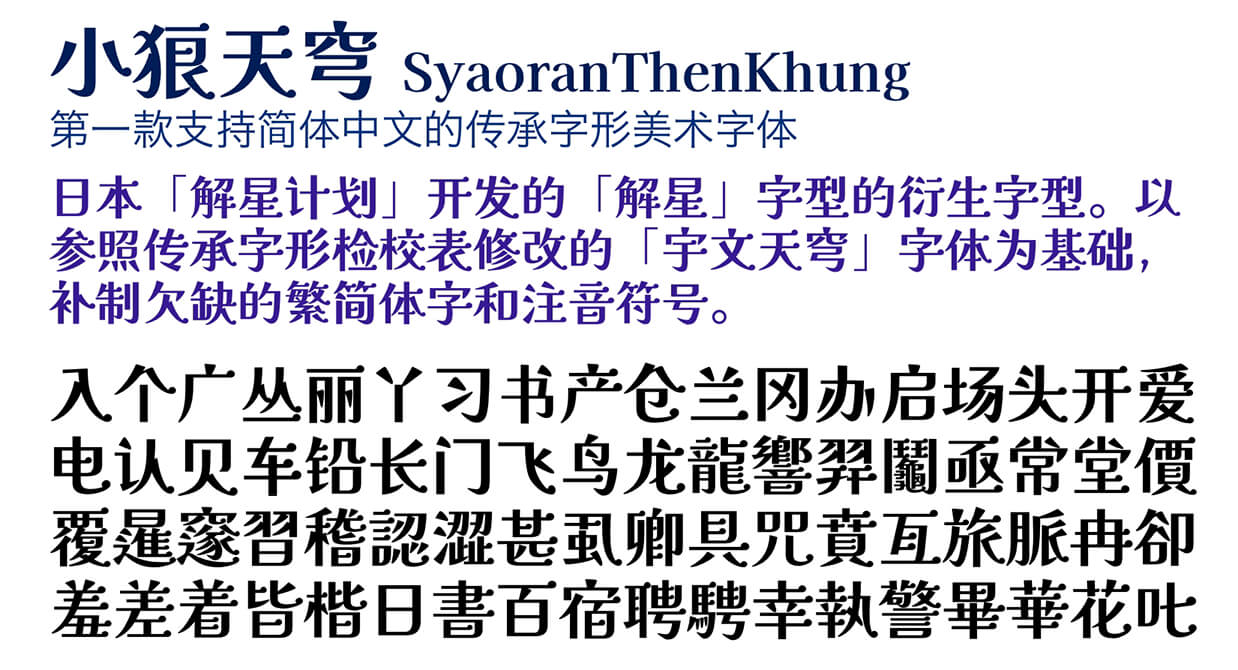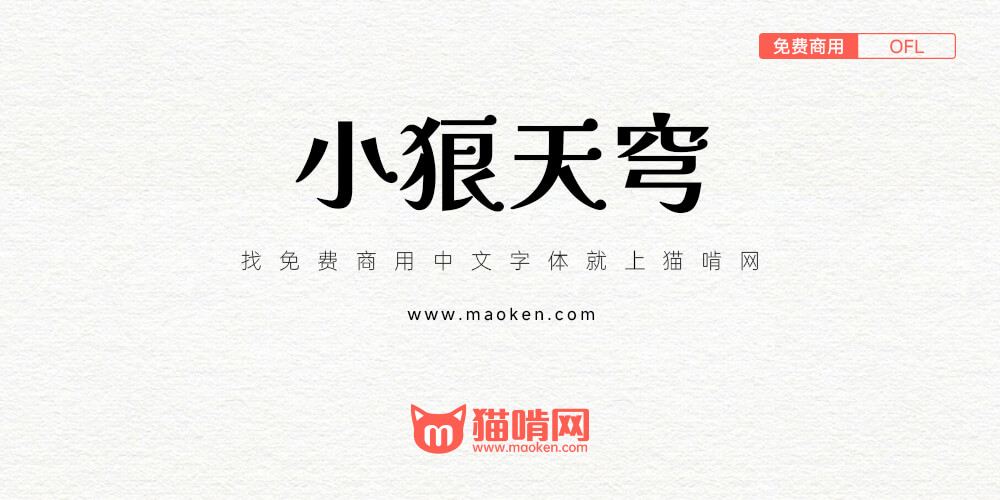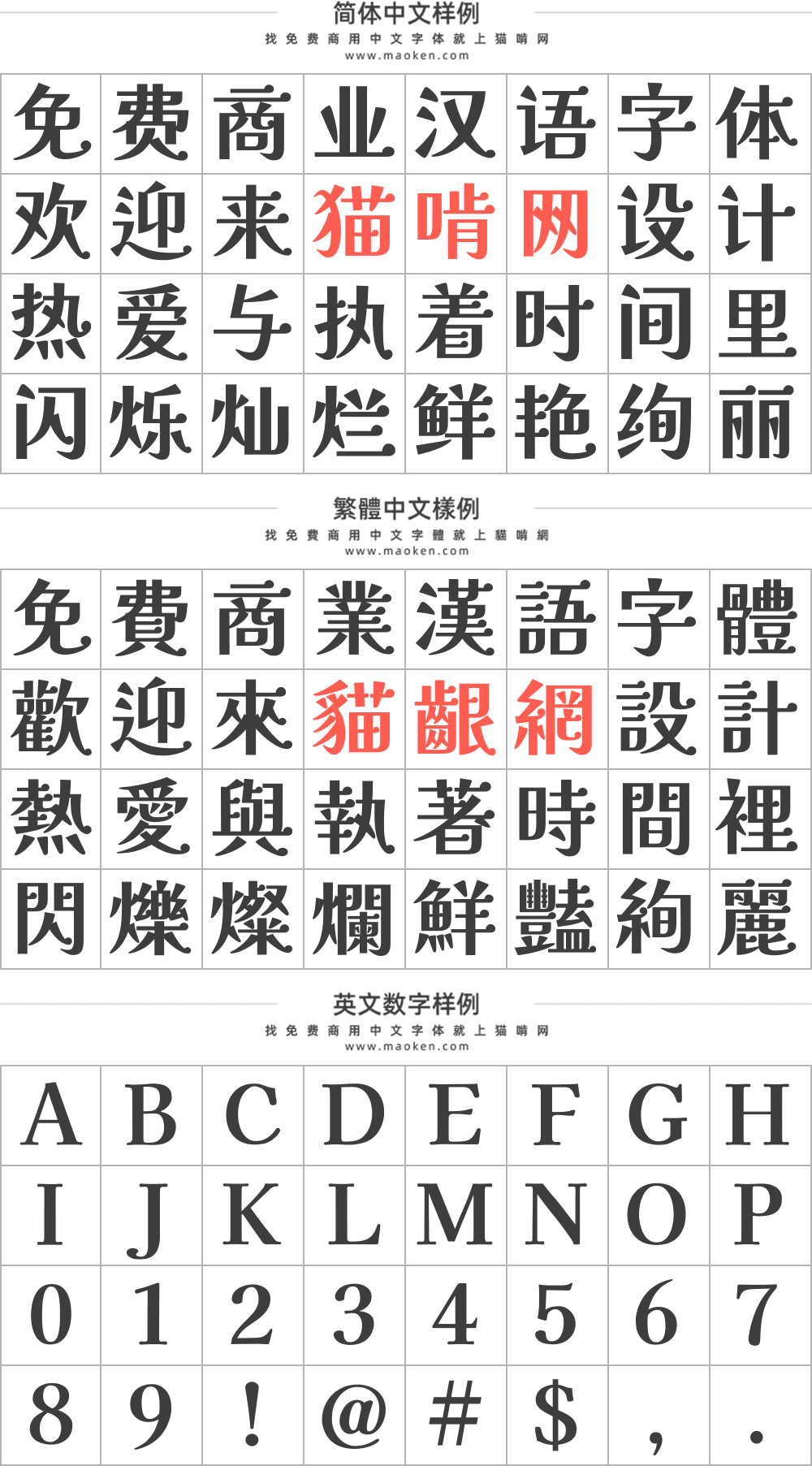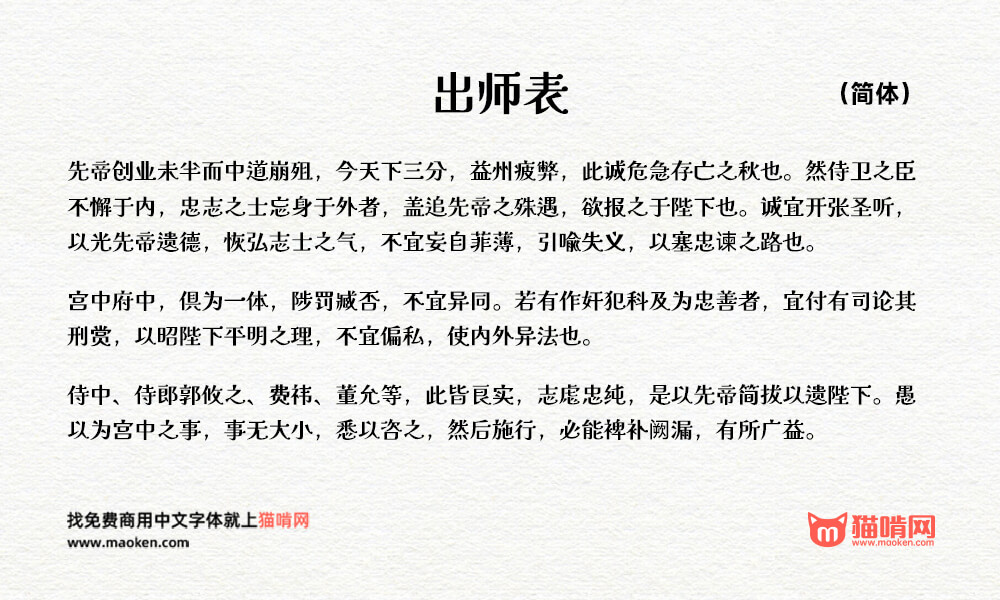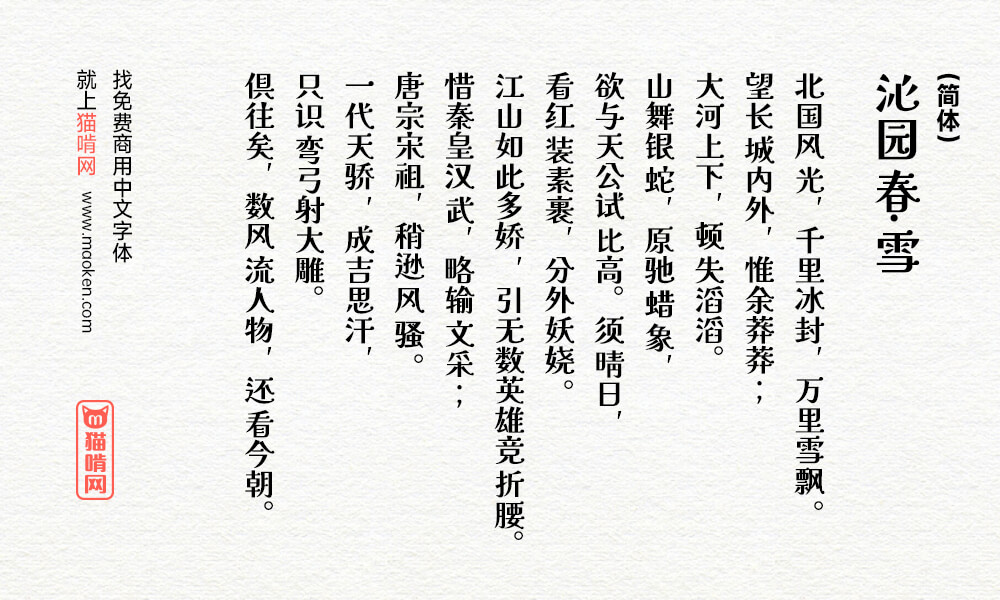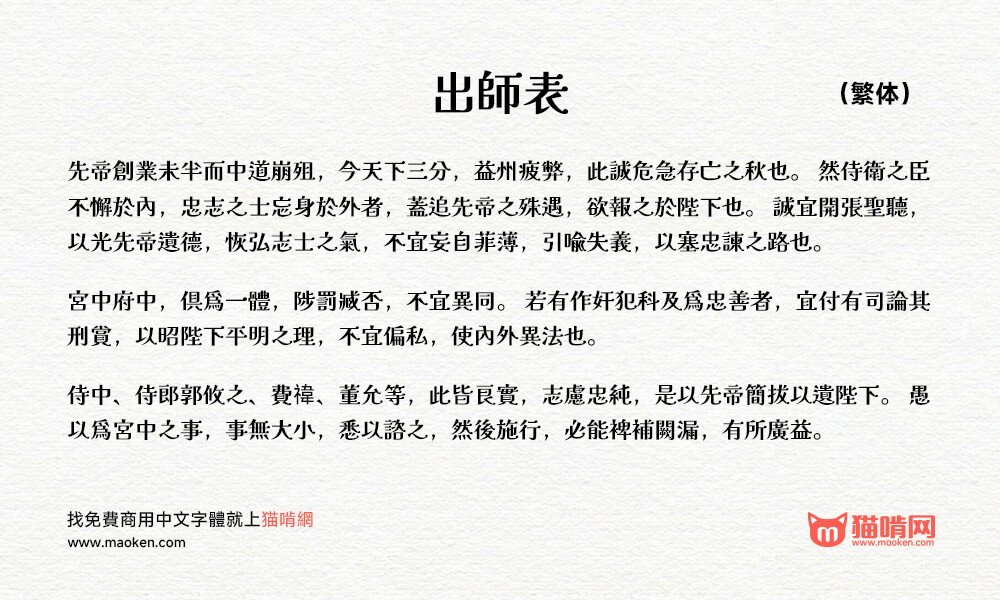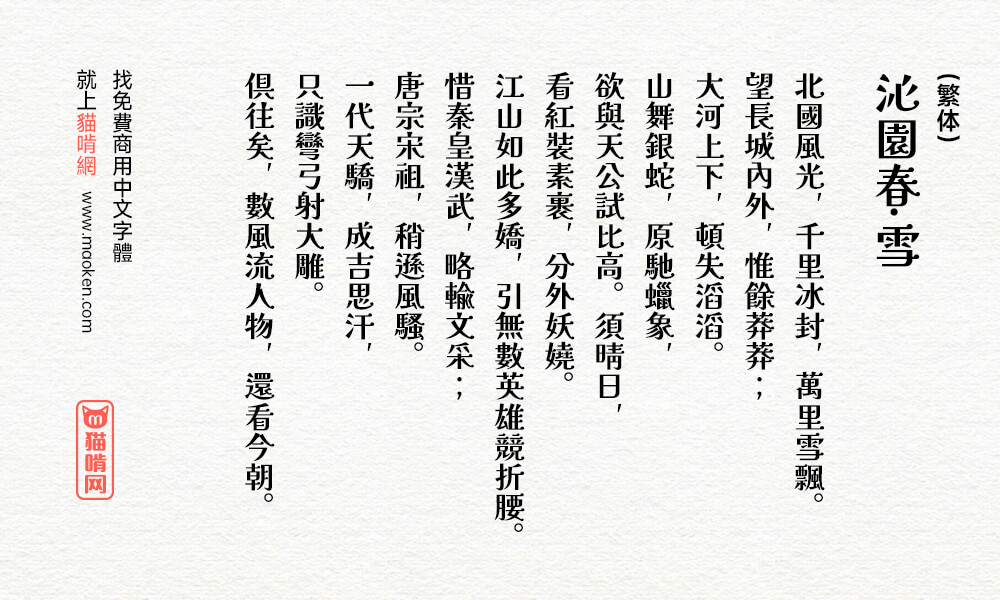
小狼天穹:第一款支持简体中文的传承字形美术字体
字体作者:躁動 (2024年06月) 字体字重:1个
小狼天穹是基于日本[ 解星计划」开发的「解星」字型的衍生字型。 以参照传承字形检校表修改的「宇文天穹」字体为基础,补制欠缺的繁简体字和注音符号。
• 小狼天穹第一版正式发布。
路径一起打出来“经”是错的,单独“经”没有问题?
这个字体的明黑风格设计非常惊艳,让我想到了另一款日文字体“FOT-Skip(スキップ)”,只是这个字体作为艺术字体加了许多装饰性设计,如果有大佬能照着这个风格再修改出一个标准黑体字的版本的话,完全可以成为简体中文版的スキップ或者金萱了
字体名称:SyaoranThenKhung